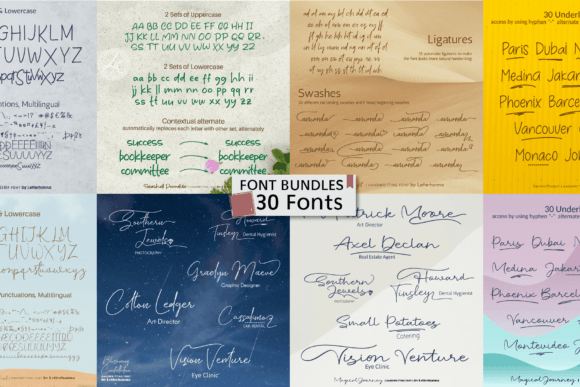
30 Handwritten Bundle Font
أضف لمسة إبداعية وعصرية إلى تصميماتك مع حزمة خطوط مكتوبة يدويًا التي تضم 30 خطًا فريدًا ومميزًا!
هذه المجموعة هي الخيار المثالي لمشاريع التصميم التي تحتاج إلى أنماط أنيقة وشخصية.
مميزات المنتج:
• 30 خطًا متنوعًا: تشمل أنماط مكتوبة يدويًا تجمع بين الأناقة والبساطة لتناسب مختلف المشاريع.
• عالية الجودة: خطوط بدقة احترافية تضمن وضوح الكتابة وجمالها على جميع الوسائط.
• استخدام متعدد: مثالية لتصميم الشعارات، الدعوات، البطاقات، منشورات السوشيال ميديا، وأكثر.
استخدامات المنتج:
• تصميم الشعارات والهوية البصرية.
• إنشاء دعوات الزفاف والبطاقات الشخصية.
• إضافة لمسة فنية للمدونات أو منشورات وسائل التواصل الاجتماعي.
لماذا تختار هذه الحزمة؟
• تجمع بين القيمة والجودة مع مجموعة خطوط متنوعة.
• تضفي أسلوبًا فريدًا وشخصيًا على مشاريعك.
• توفر لك الوقت مع خطوط جاهزة للاستخدام الاحترافي.